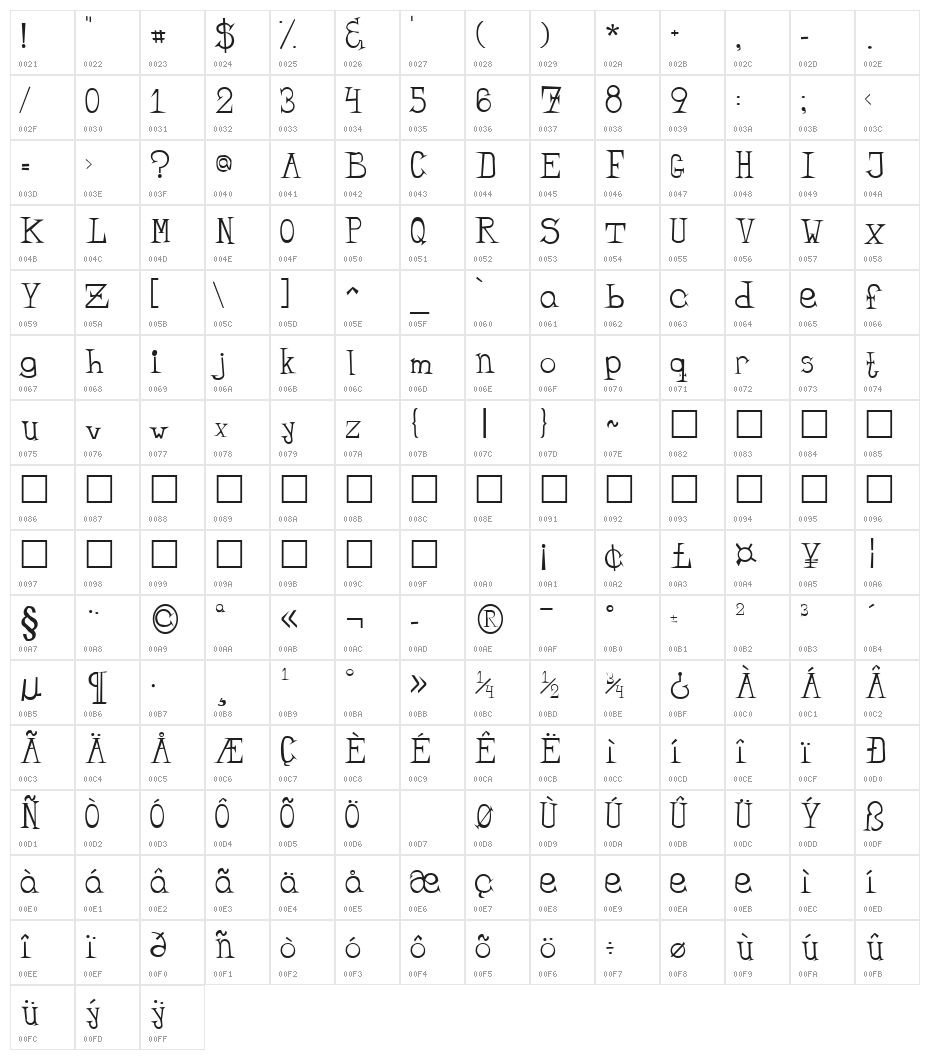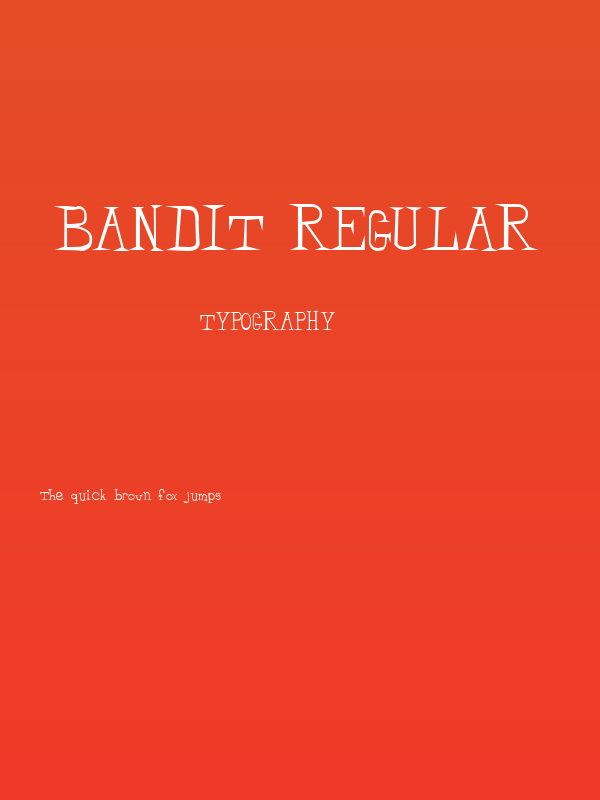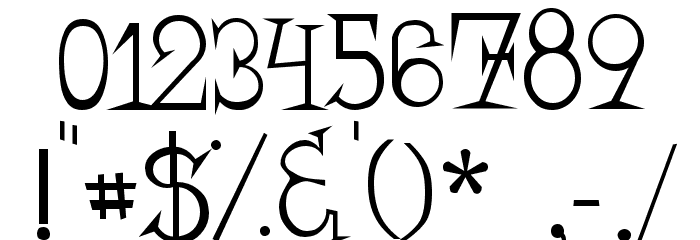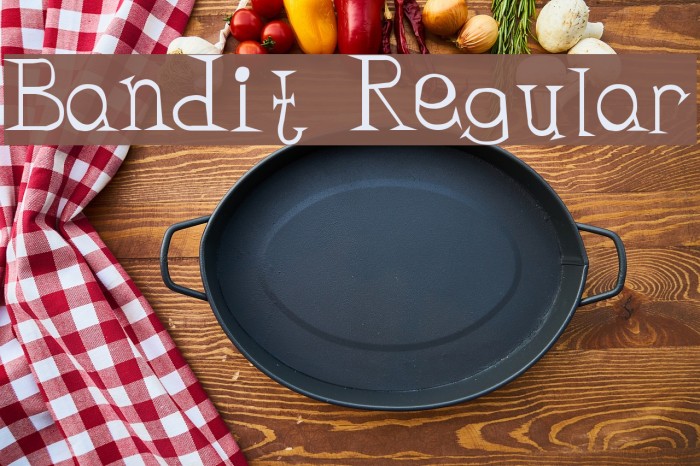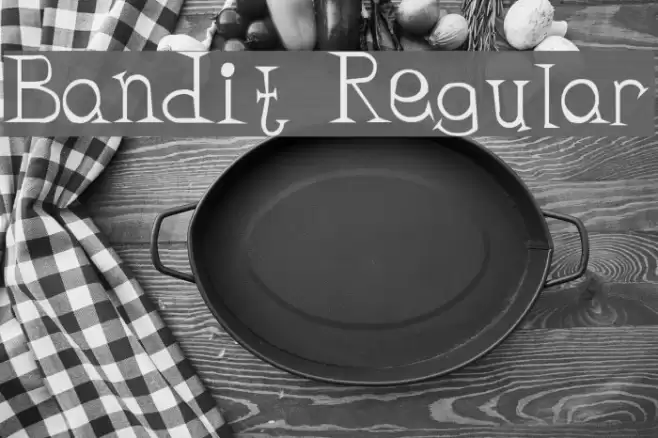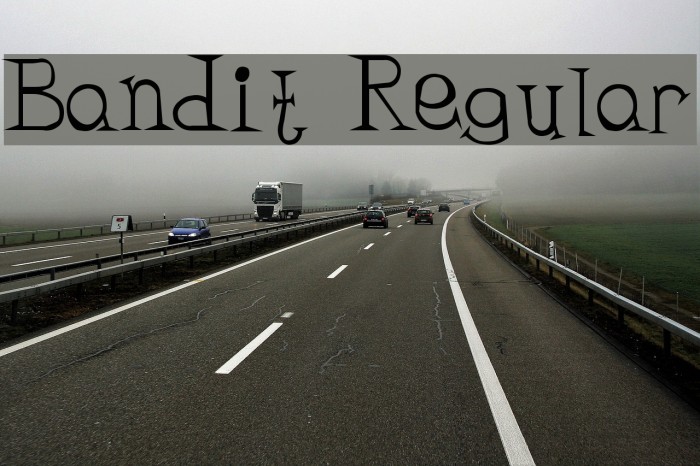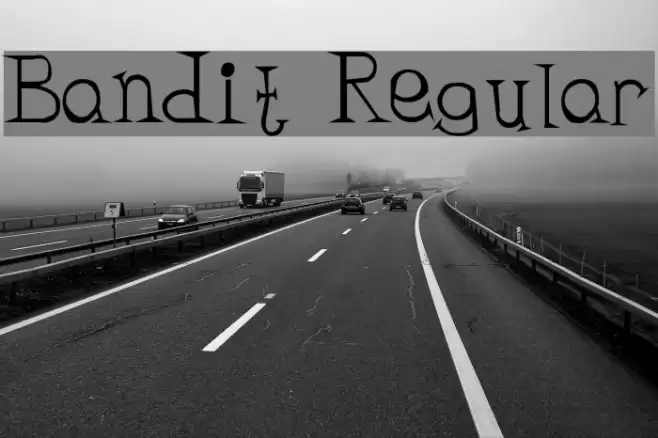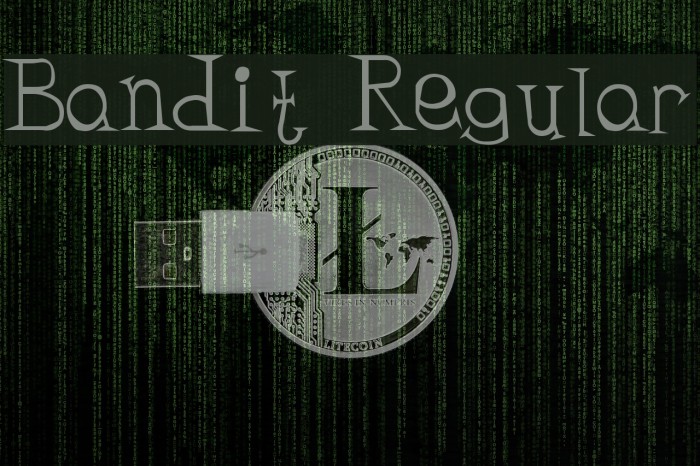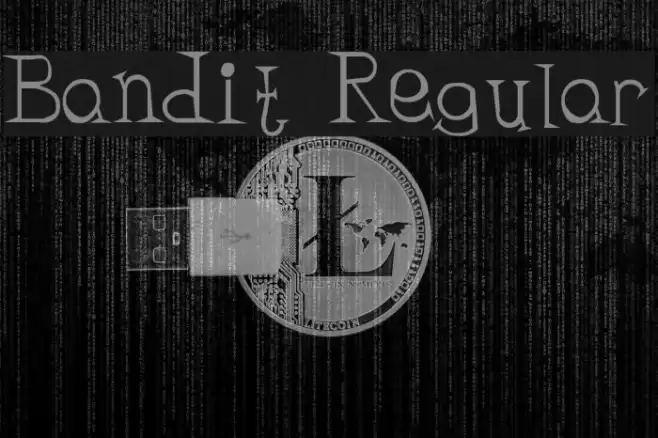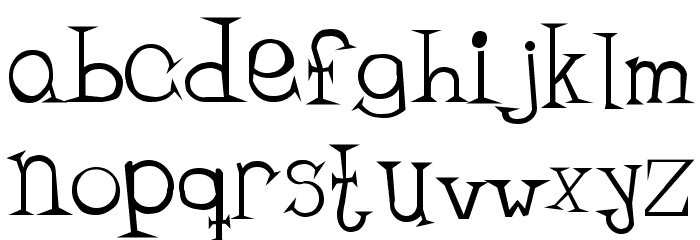
Bandit Regular Font
✎ Quirky
| Proiecte propuse | Ideal for creative projects such as posters, album covers, children's books, and branding that seeks a unique and adventurous look. |